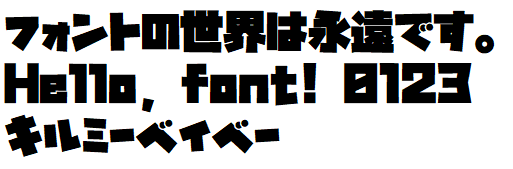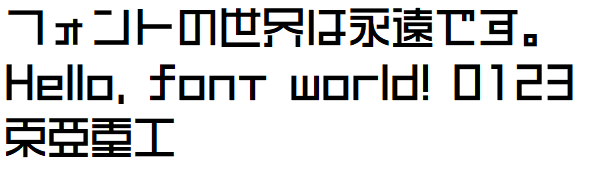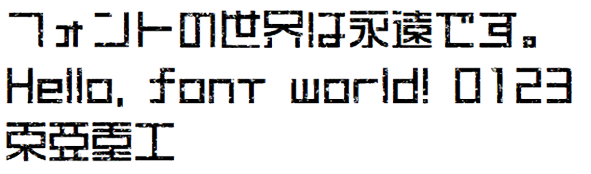
ComicStudio-GA
- 漫画の台詞に使われる書体
- アンチック体
- 1935年写研による写植書体
- 肉太な仮名
- slab-serif、築地明朝活字、千社札文字を参考にて作られた
- ゴシック体の漢字と組み合わせることにより、文字の濃淡が一定になる
ComicStudio-GT
- 漫画のスピーカー音声などに使われる書体
- タイポス
- 1962年タイプバンクによる写植書体
- ゴシック体か明朝体しかなかった時代に登場
- 新書体ブームのきっかけ
- 若者向けの雑誌に盛んに使われた
- 仮名のみだったが発売と共に大ブームに
- 漢字の揃った総合書体「タイポスオールマイティ」も発表された
源暎アンチック v5 Medium
- 漫画の台詞に使われる書体
- 漢字:Adobe『源ノ角ゴシック』
- 仮名:アンチック体
源暎ラテゴ v2 Medium
- 漫画のスピーカー音声などに使われる書体
- 漢字:Adobe『源ノ角ゴシック』
- 仮名:タイポス風
70:ドラえ文字
- 仮名、英大文字、数字
- 漫画『ドラえもん』風書体
RoundDORA+
- 組み合わせてみた
- 仮名、英大文字、数字『70:ドラえ文字』
- 漢字、英小文字『Rounded-X M+ 1p black』
キン肉マンフォント
- カタカナ(1byte)
- 漫画『キン肉マン』風書体
DEATH FONT
Death Font
- 英数字
- 漫画『DEATH NOTE』リューク手書き風書体
Bizareadventure
i2f First Gundam
GetterFont
TypoBokanKT
- カタカナ(1byte)
- アニメ『タイムボカン』風書体
ロボダッチ
Evit-logo
- カタカナ(1byte)
- 漫画『名探偵コナン』風書体
Evit-logo+
- 組み合わせてみた
- カタカナ『Evit-logo』
- その他『M+ 1p black』
自由の翼フォント
- 森下浩司『M+ FONTS』改訂
- 漢字174文字+その他68文字を改訂
- アニメ『進撃の巨人』第二期オープニング風書体
東亜重工 R
- 第二水準まで
- 漫画家・弐瓶勉の作品に登場する文字
- 字面として正方形に見えるように調整
- 複雑な線を簡略・一体化
東亜重工 GRUNGE
- 第二水準まで
- 上記『東亜重工』に汚れ加工を施したもの
GN-キルゴUかなNA
- 漢字部分はcoz『M+ FONTS』を素材とした3,000文字以上
- 仮名の違う『~NB』『~O』あり
- 漫画『キルミーベイベー』風書体
GN-きんいろサンセリフ
- 漫画『きんいろモザイク』風書体
けいふぉんと
- ©Do-Font
- すもももじ
- 漢字部分はAdobe『源ノ角ゴシック』、coz『M+ OUTLINE FONT』、MM『源真ゴシック』
- 漫画『けいおん!』風書体
FriendsFu Regular
- ©kyoyababa Design
- GitHub
- ひらがな、カタカナ
- アニメ『けものフレンズ』風書体
Kemonoteki(けものてき)
- ©Neon
- BOOTH